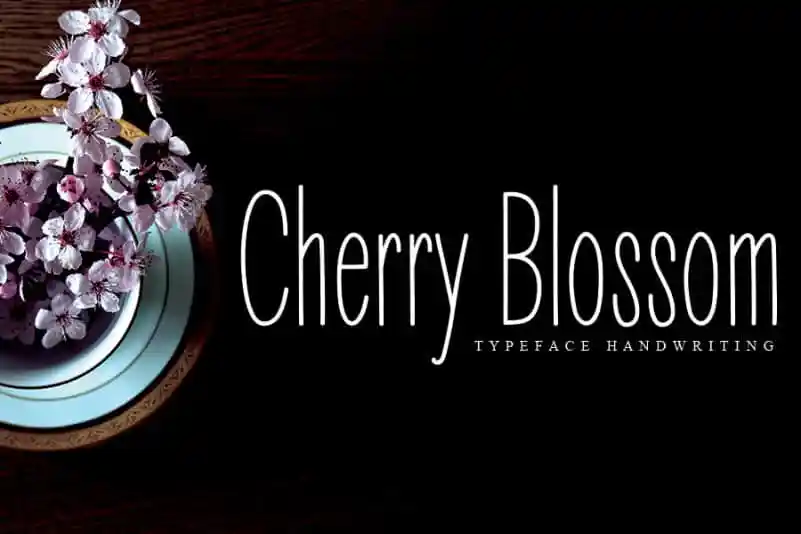
A Cherry Blossom Display Font é uma escolha perfeita para os designers que buscam simplicidade e clareza no seu trabalho. Essa fonte sans-serif natural e elegante combina perfeitamente com diversos projetos de design, proporcionando um resultado impecável em rótulos, materiais gráficos ou até mesmo elementos digitais. A sua natureza simples e limpa permite que você use essa fonte para criar ideias criativas e atractivas sem ter que se preocupar com os detalhes exagerados. Este é mais do que uma ferramenta de design; ele é um parceiro confiável na sua jornada de criação, pronto para adaptar-se a todos os tipos de projetos em uma variedade de formatos e estilos de design. Com o Cherry Blossom Display Font da designer andikastudio, transforme suas ideias num resultado profissional e único.